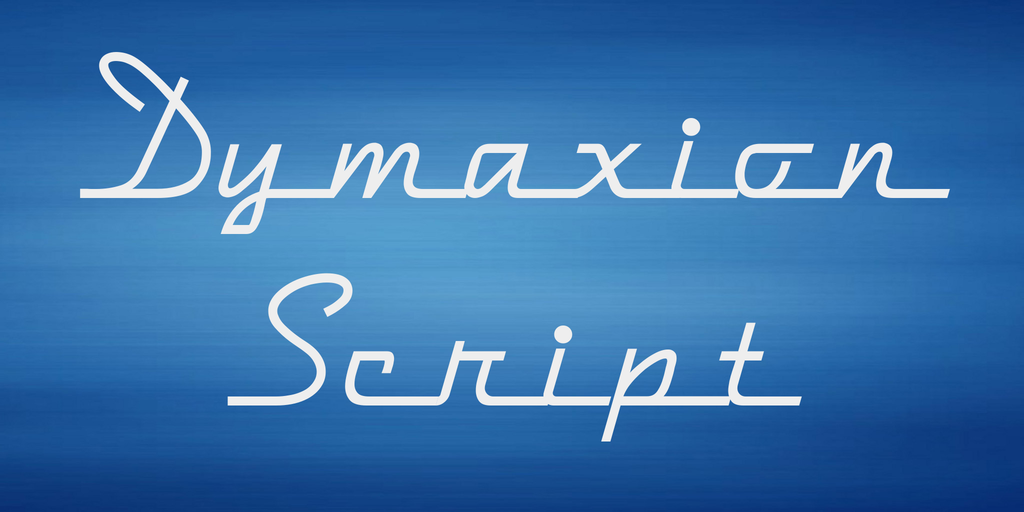
Dymaxion Script Font – Fonte Grátis
Dymaxion Script Font
A Dymaxion Script Font é uma exótica escolha para designers que desejam adicionar um toque único a seus projetos. Seu nome remete à conceito do conceituado R. Buckminster Fuller, conhecido por sua criatividade inovadora e visionária no design de veículos futuristas, mapas inusitados e até mesmo uma banheira deslumbrante. Esta fonte pertence a uma categoria chamada Blackletter Fonts, um tipo especial de letra que remonta à antiguidade germânica. Os criadores desta fonte escolheram nomeá-la em homenagem aos seus conceitos arquitetônicos e projetos visionários da década de 1930, atraindo-nos para uma compreensão do design fluido e aerodinâmico que movimenta o espectro visual. Como sua descrição original sugere, esta fonte é fluida, moderna e ativa, se adequando perfeitamente aos projetos que buscam um enfoque atraente e distinto. Seja para criar um logotipo visionário ou uma peça de design gráfico sofisticada, a Dymaxion Script Font certamente fará sua aparição ser notável.